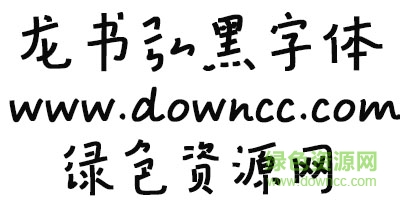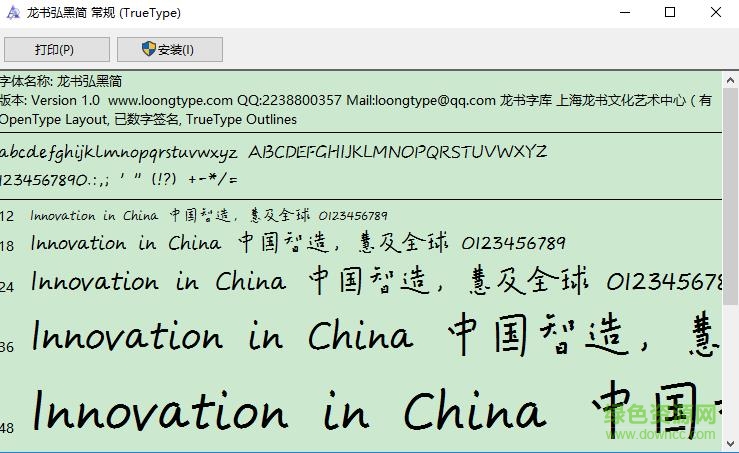
龍書弘黑字體是一款非常實用的手寫體,這款字體筆畫流暢,讓文字更加生動,非常適用于廣告設(shè)計和手寫藝術(shù)等方面,感興趣的朋友歡迎來綠色資源網(wǎng)下載體驗!
各個筆劃寬度雖是大致相等,但不是絕對的,在處理上不能強求一律,否則筆劃多的字必然擁塞寫不下,筆劃少的則顯得空,所以應(yīng)在長與短、橫與豎、筆劃粗與細(xì)之間,作適當(dāng)?shù)恼{(diào)整,達(dá)到整體上的均勻諧調(diào)。